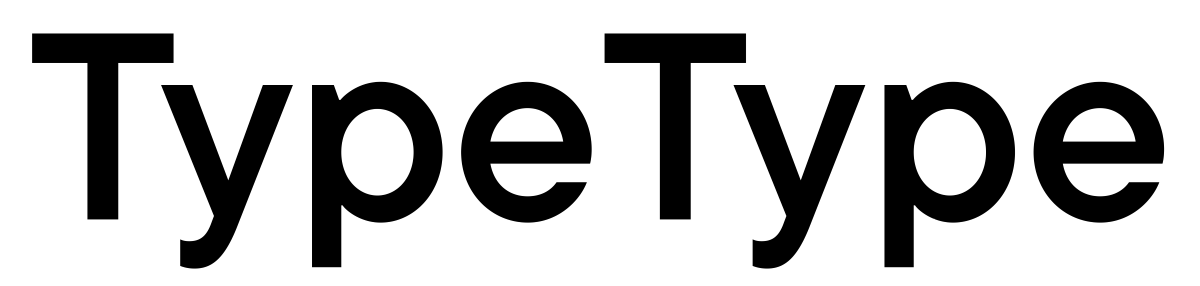
TypeType 是一家国际字体设计工作室,全球规模最大的字体设计机构之一。我们专注于字体设计,并提供定制化设计、字体优化及其他专业服务。 TypeType 字体库包含 75+ 款商用字体,涵盖各种风格:标题字体、正文字体、衬线体、无衬线体、手写体、粗衬线体、轮廓字体和等宽字体等。其中许多字体支持可变字体(Variable Fonts)技术,用户可灵活调整字重、字宽、斜度等参数。 我们持续优化并更新所有字体,确保其符合当代技术与审美标准。TypeType 字体均配备实用的 OpenType 功能,并提供广泛的语言支持,尤其涵盖多种西里尔语系版本。 全球众多知名品牌信赖我们的字体,包括 Tom Tailor、优衣库、卡通网络、DoorDash、Telefónica、CBSN、Vogue、美泰、Intercom 等。 我们致力于推动字体设计领域的发展,因此积极参与教育项目:发布文章、播客与视频教程,举办线上研讨会,与教育机构及高校合作,并为学生提供实习机会。 TypeType 字体屡获国际顶级设计奖项,包括红点奖、Granshan 设计奖、Muse 创意奖、Workspace 设计奖、Indigo 设计奖等。